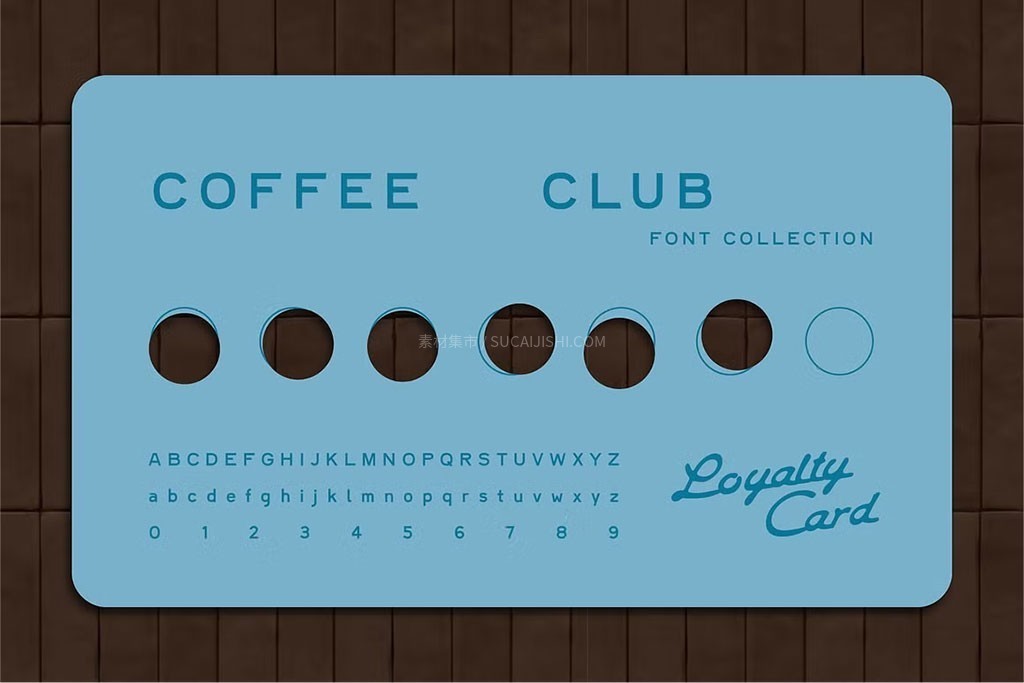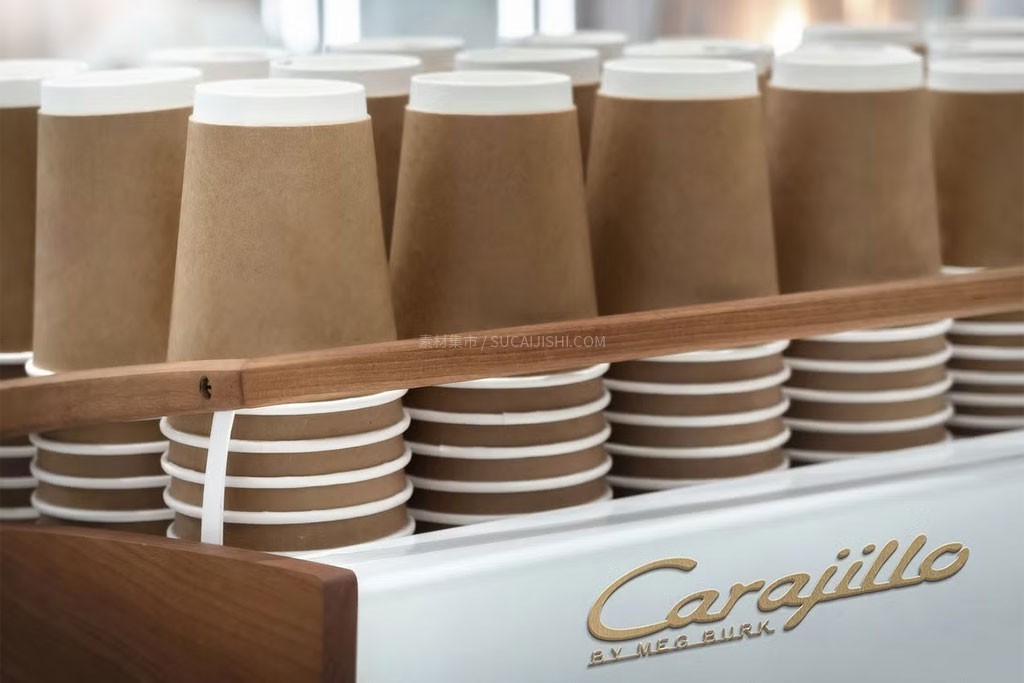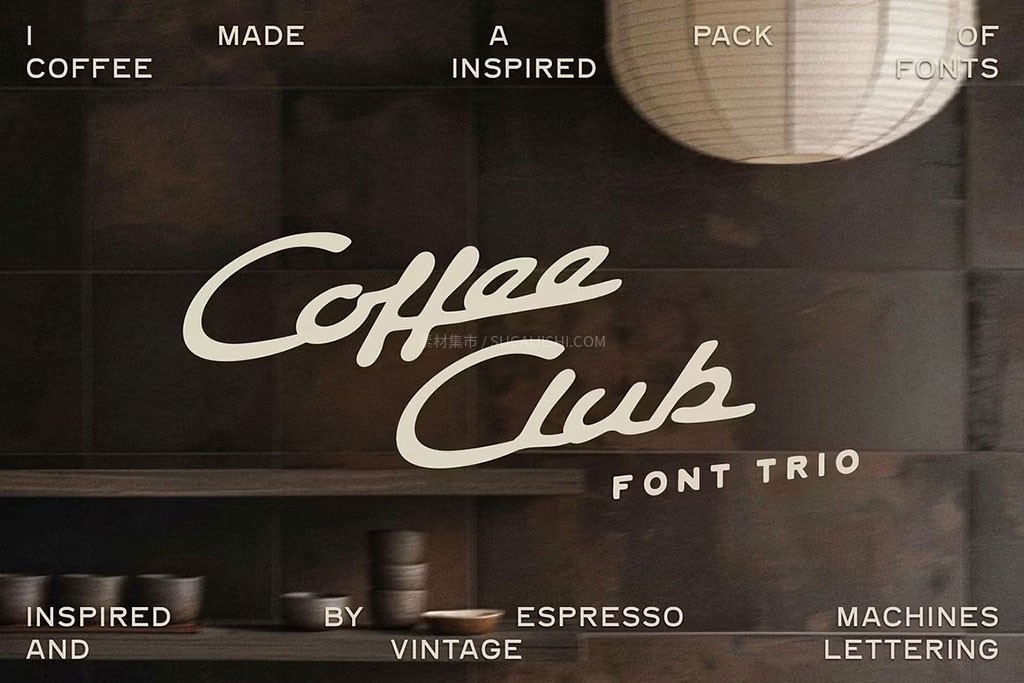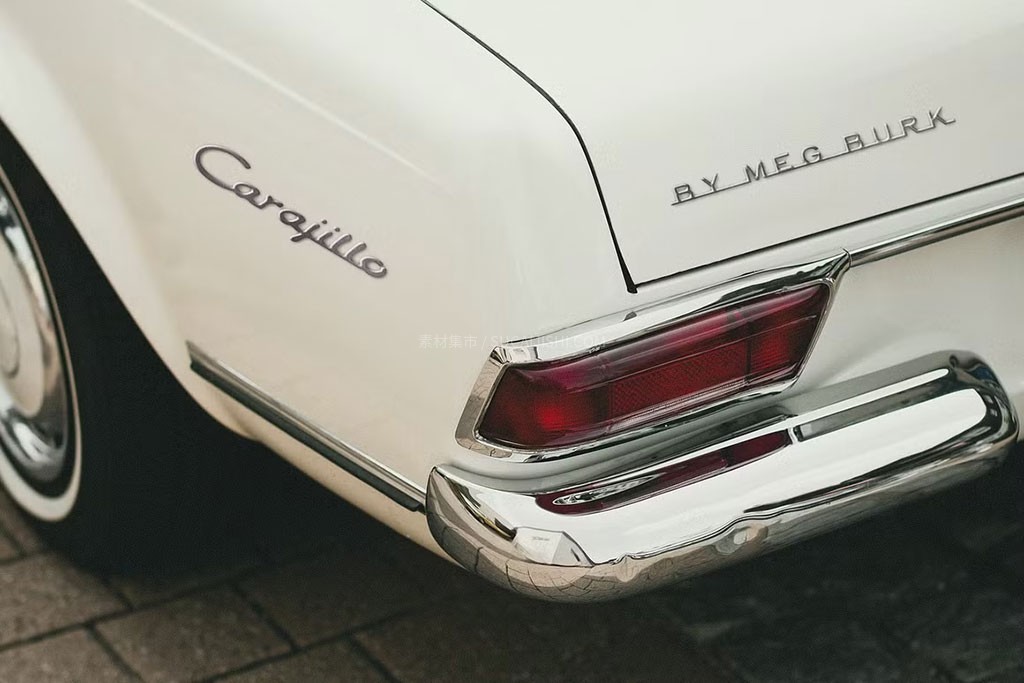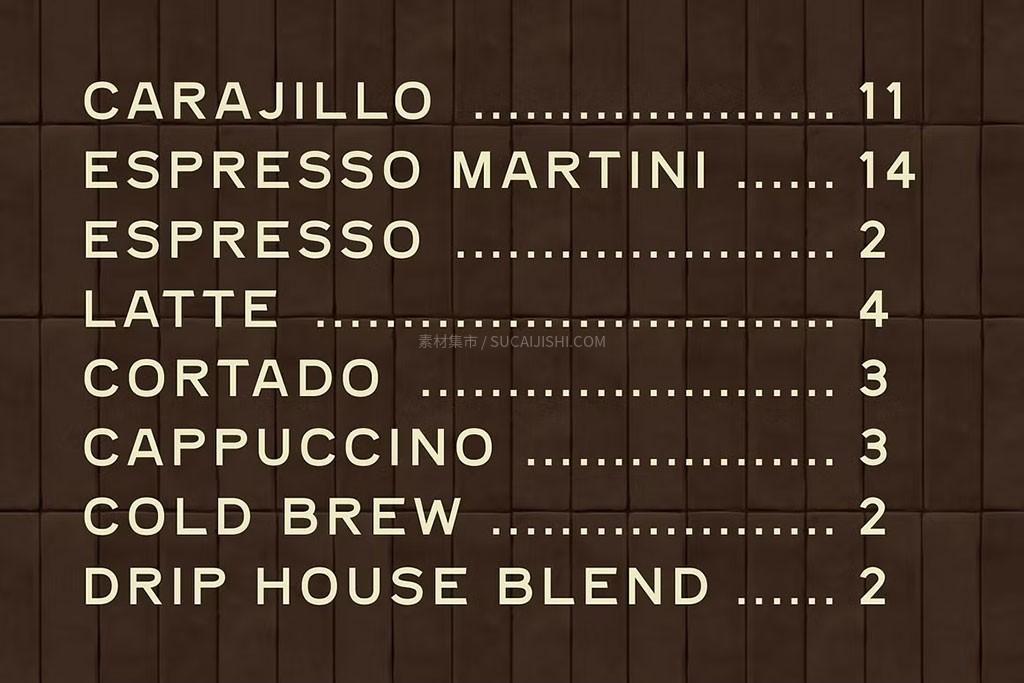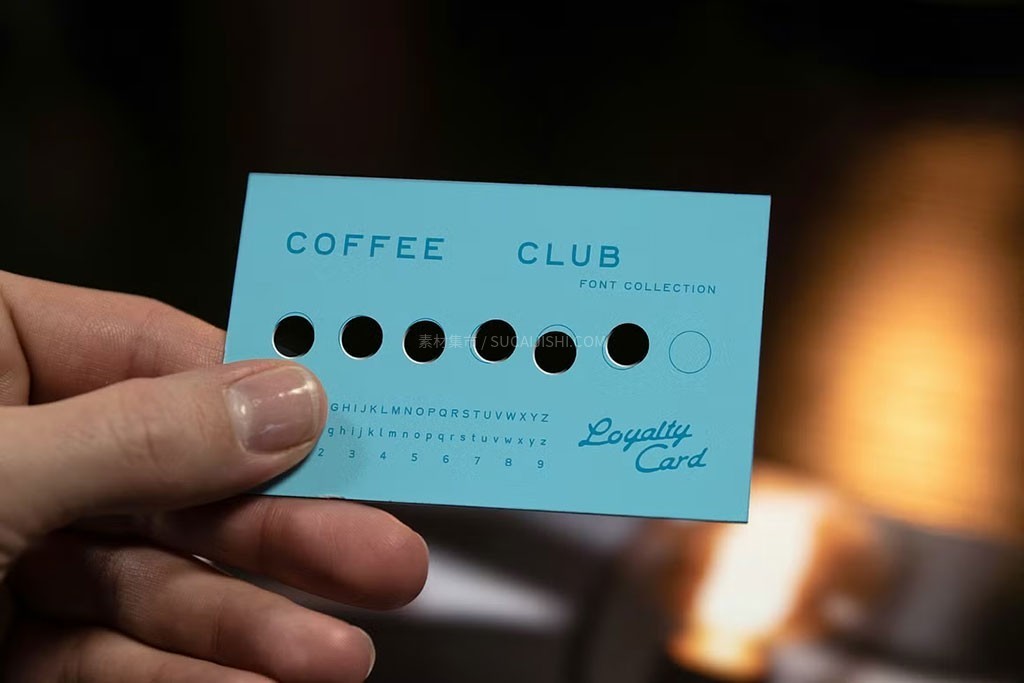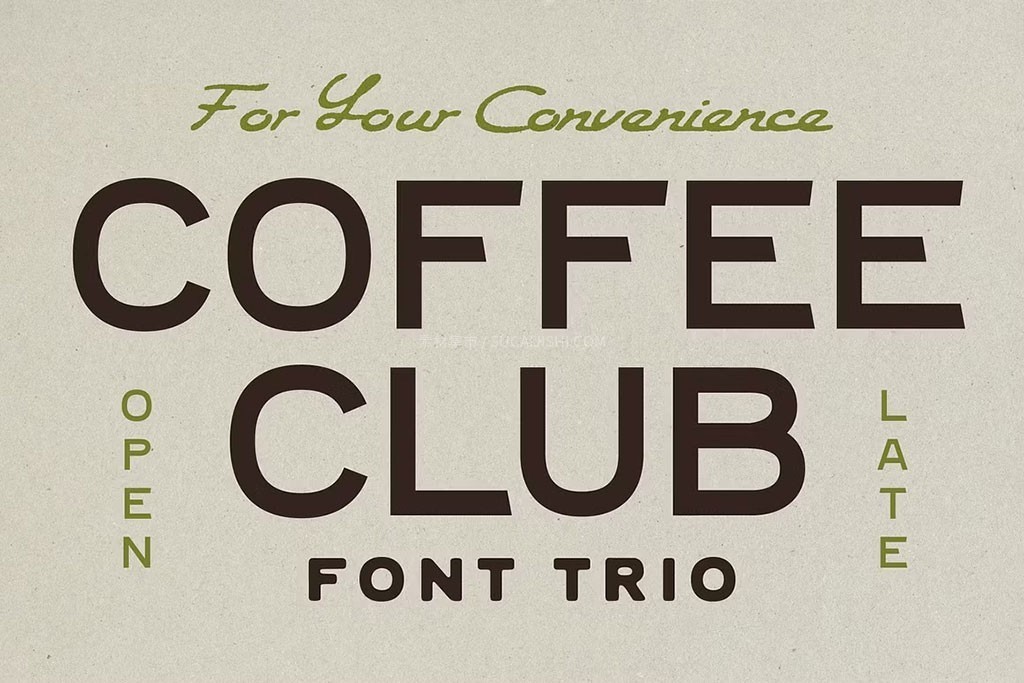
Carajillo复古铭牌手写字体
全套包含7种不同的风格,所有字符都是纯手绘后精细打磨的,拒绝死板的机械感,满满的都是真实的手工温度。适用咖啡馆/餐饮品牌形象设计、复古Logo、菜单排版、包装设计、独立门店视觉、活动海报、社交媒体图文等。
Carajillo:浪漫粗犷的复古手写体,自然又吸睛,做主标题简直绝了;
Cappuccino(5种变体):稳健严谨的无衬线字体家族,排版和做菜单的最佳拍档,让主标题更加突出;
Cowboy:带点狂野质感的休闲手绘无衬线体,特别适合用来做Slogan或活动视觉。